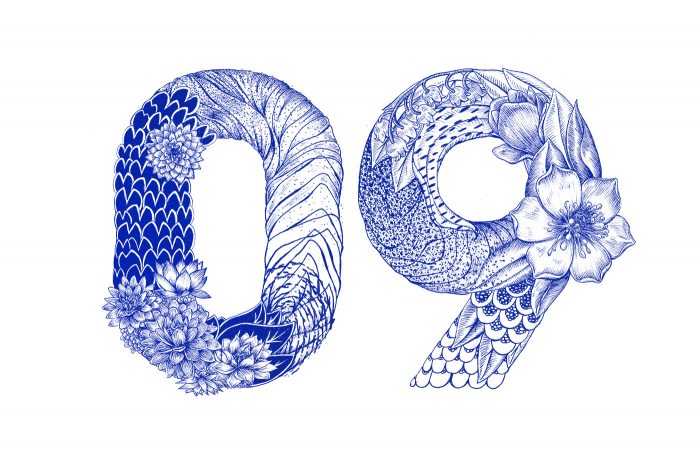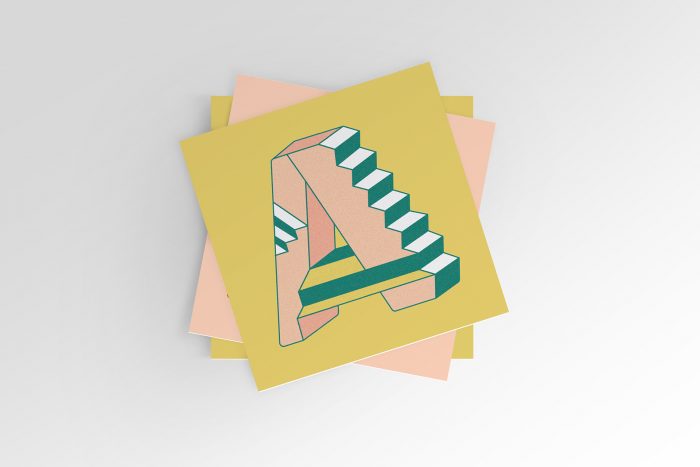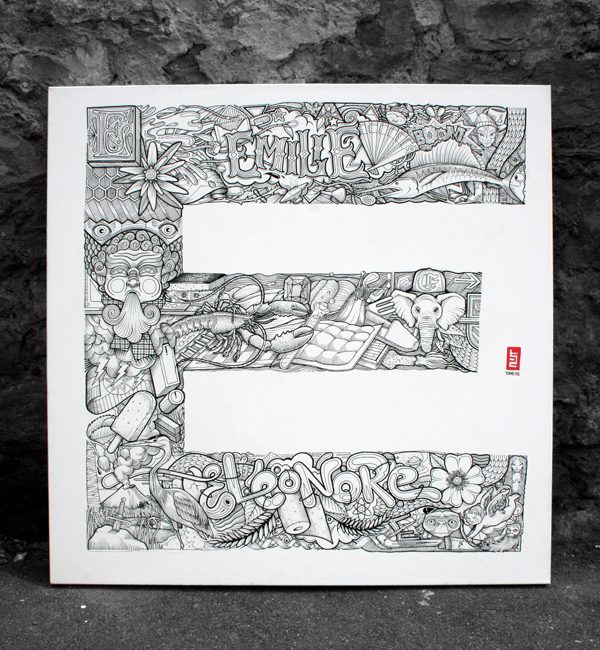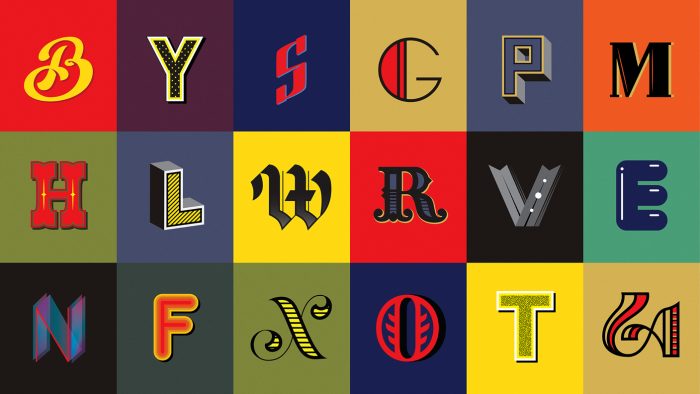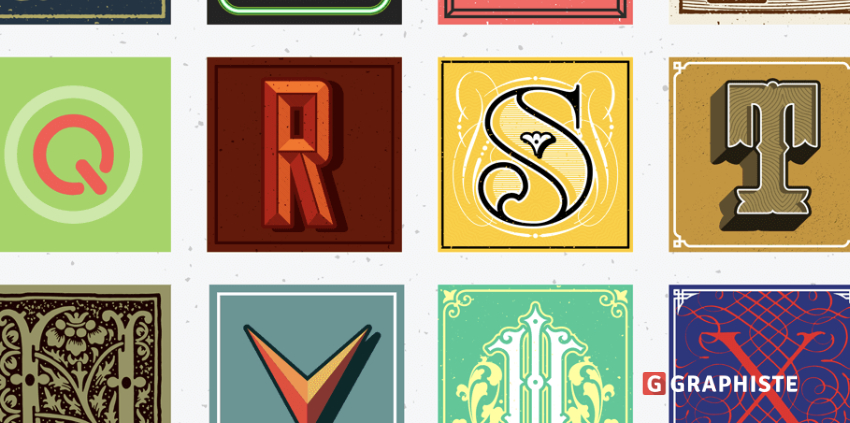
Typographie : comment utiliser la lettrine en 2020 ?
Dans le domaine de la mise en page, les effets de style règnent puis disparaissent.
L’histoire ne les oublie pourtant jamais vraiment et on voit régulièrement certaines présentations refaire surface. Il en est ainsi du Letterpress, qui s’impose de plus en plus dans les imprimeries, mais également des lettrines.
Mais d’où proviennent-t-elles ? Dans quel cas les utiliser ? Et quelle place ont-elle aujourd’hui ?
L’apparition de la lettrine est bien antérieure à celle de l’imprimerie puisque les premières d’entre elles remontent à l’époque médiévale.
Des artistes dédiés, bien plus que des copistes, consacraient de longues heures à ces enluminures qui réveillaient les textes pour les mettre en valeur. Travail de dorure, de dessin, de miniaturisation…
Il y avait de l’imagination dans la lettrine. Elle racontait déjà presque ce que le texte suivant allait dire. A notre époque, on pourrait considérer que les intertitres les remplacent… avec plus ou moins d’efficacité. En effet, alors que les lettrines ont presque disparu du paysage des textes imprimés, elles ont encore beaucoup de choses à dire.
Comme pour toutes les bonnes choses, il ne faut pas abuser des lettrines. En placer à tort et à travers dans tous vos documents amoindrirait considérablement leur impact.
De plus, une bonne lettrine occupe le terrain. Un texte trop court placé à côté d’elle paraîtrait encore plus petit qu’il ne l’est déjà.
Vous utiliserez donc plutôt des lettrines pour :
Il y a plusieurs façons d’utiliser les lettrines.
Dans le cas où vous souhaiteriez les employer dans une thèse, rapport de stage ou tout autre type de document où elles seraient justifiées, il est possible de les positionner à l’introduction, conclusion ainsi qu’à chaque grande partie de votre document. Pour cela, vous avez 2 options :
Les lettrines sont relativement rares dans le paysage graphique et littéraire actuel. On peut en trouver dans des mises en page travaillées pour des magazines, en général lors d’occasions spéciales.
Il va de soi qu’il s’agit ici uniquement de la lettrine « graphique », pas de la simple surexposition d’une lettre dans une police de caractère plus imposante que le reste du texte.
La lettrine s’appuie sur les techniques à l’honneur actuellement : papiers découpés, ombrages, voire collages ou travail sur la texture .
Toutes les formes de recherche peuvent être mises à l’honneur, dans ces mise en avant de lettres un peu particulières. La lettrine idéale ne sera d’ailleurs pas qu’un simple ajout graphique, elle correspondra à la tonalité du texte, comme n’importe quel support d’illustration.
N’oubliez pas :
Incluez-les dans votre mise en page, adaptez votre typographie, aérez votre texte en fonction de l’espace pris par la lettrine… Ce peut être l’occasion de réfléchir à une présentation du texte qui soit moins linéaire…